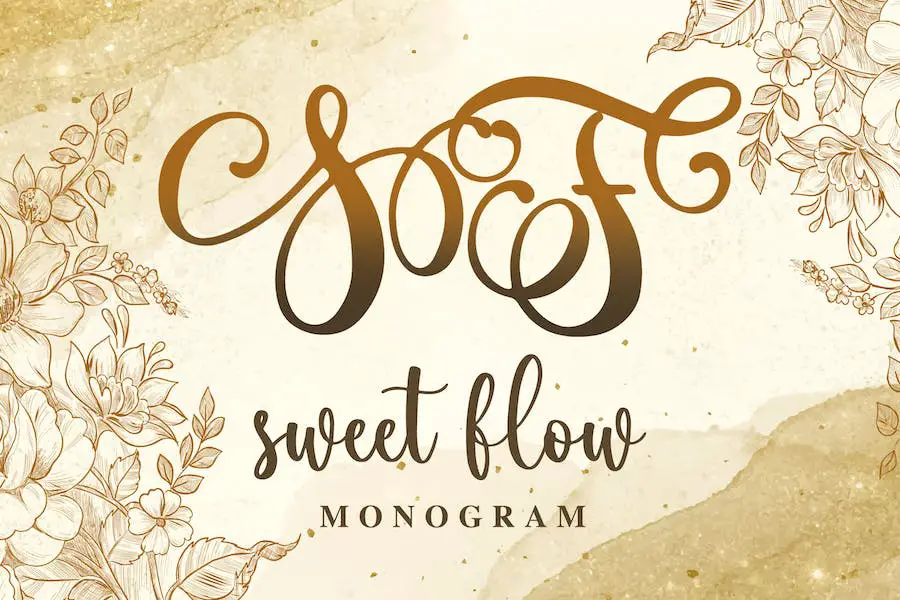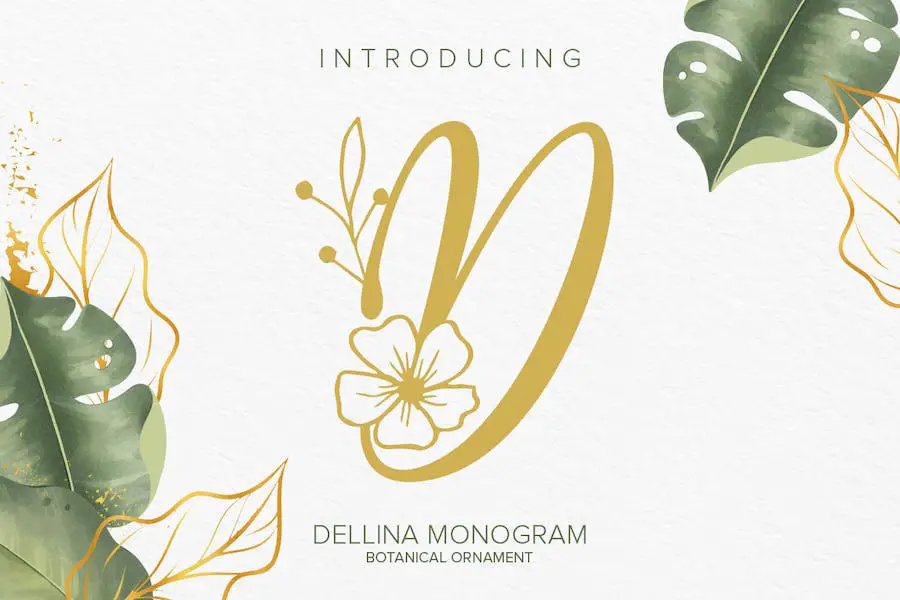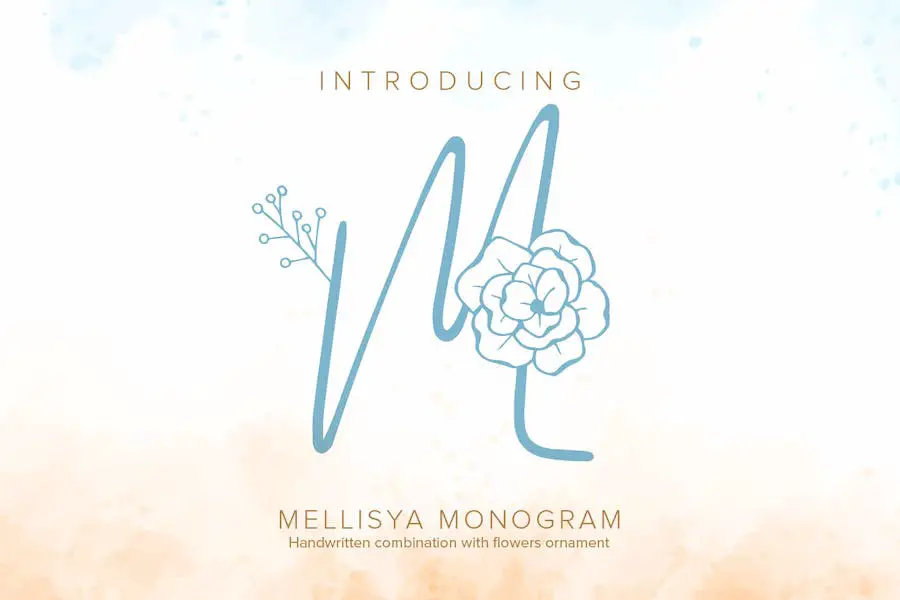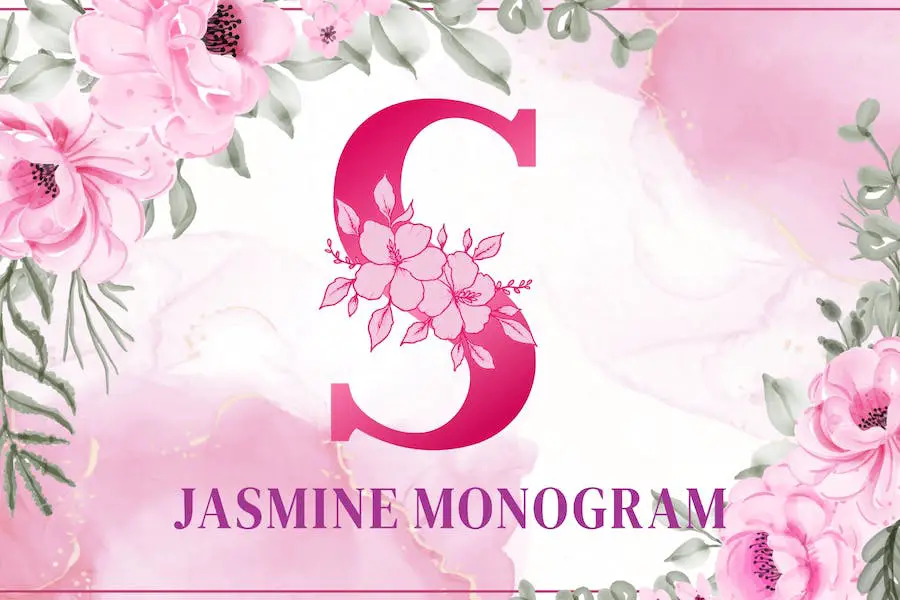
Agora, você deve estar se perguntando, por que devo considerar o uso de fontes de monograma. Bem, os monogramas têm sido uma escolha popular em design por sua elegância, sofisticação e apelo atemporal.
Eles adicionam um toque pessoal a qualquer projeto e podem elevar instantaneamente a sensação geral do seu design.
Neste artigo, não apenas mostraremos 39 das melhores fontes de monograma, mas também forneceremos algumas estatísticas e fatos interessantes sobre cada fonte.
Vamos nos aprofundar em suas origens e nos designers por trás deles, e dar a você um vislumbre de como eles podem ser usados de maneira eficaz em vários projetos de design.
Portanto, esteja você trabalhando em um logotipo, convite de casamento ou materiais de marca, essas fontes de monograma certamente inspirarão e aprimorarão seu trabalho.
Clarissa Monograma
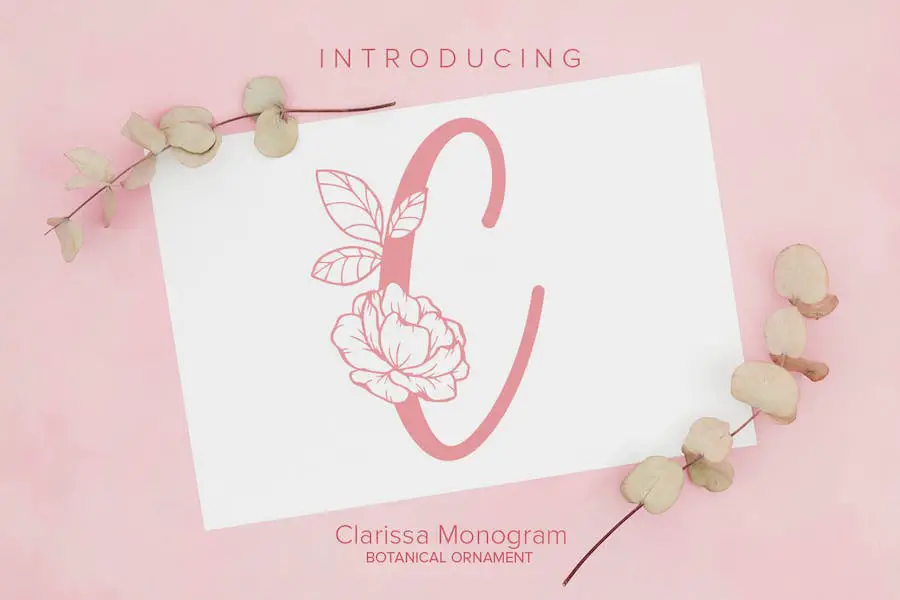
Apresentando Clarissa Monogram, uma fonte decorativa doce e delicada que pode adicionar uma sensação autêntica aos seus projetos de design.
Esteja você criando convites de casamento deslumbrantes, belas artes estacionárias, postagens de mídia social atraentes ou cartões fofos, essa fonte com certeza elevará seus designs.
Clarissa Monogram é perfeita para designers gráficos que procuram uma fonte que aprimore seus projetos e lhes dê um toque único. Com seu toque autêntico e design delicado, essa fonte é versátil e pode ser usada para diversos fins.
Caligrafia do monograma
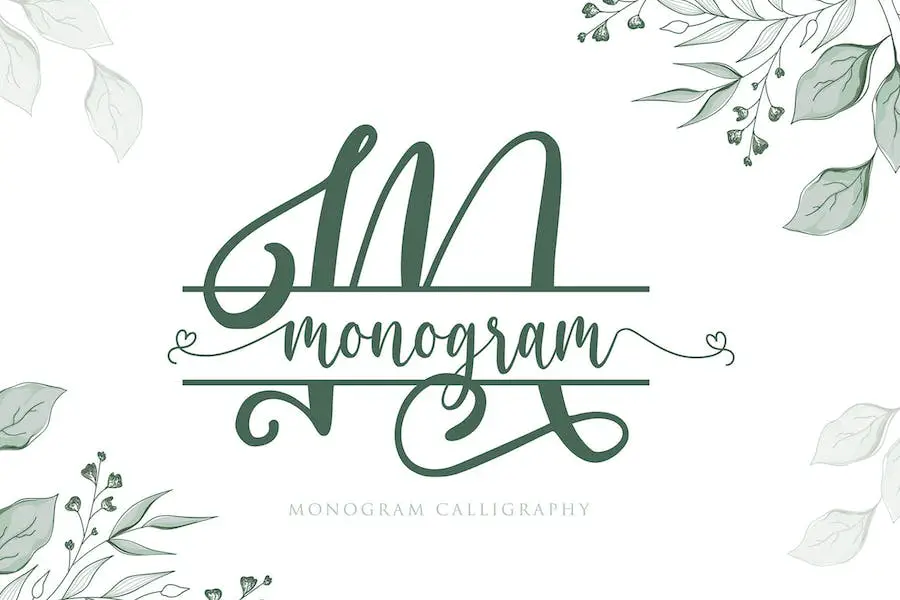
Monogram Calligraphy é uma fonte requintada que exala romance e elegância atemporal. Ele combina perfeitamente a caligrafia tradicional com elementos de design modernos para criar um monograma impressionante.
A melhor parte da caligrafia de monogramas é sua versatilidade. É compatível com vários softwares, como Google, Adobe, Word, Canva, Circuit e Figma, e até mesmo para desenhos de tatuagens e logotipos personalizados no Instagram.
Seja você um designer gráfico trabalhando em um projeto profissional ou um indivíduo procurando aprimorar sua marca pessoal, essa fonte é perfeita para você.
Casa de fazenda
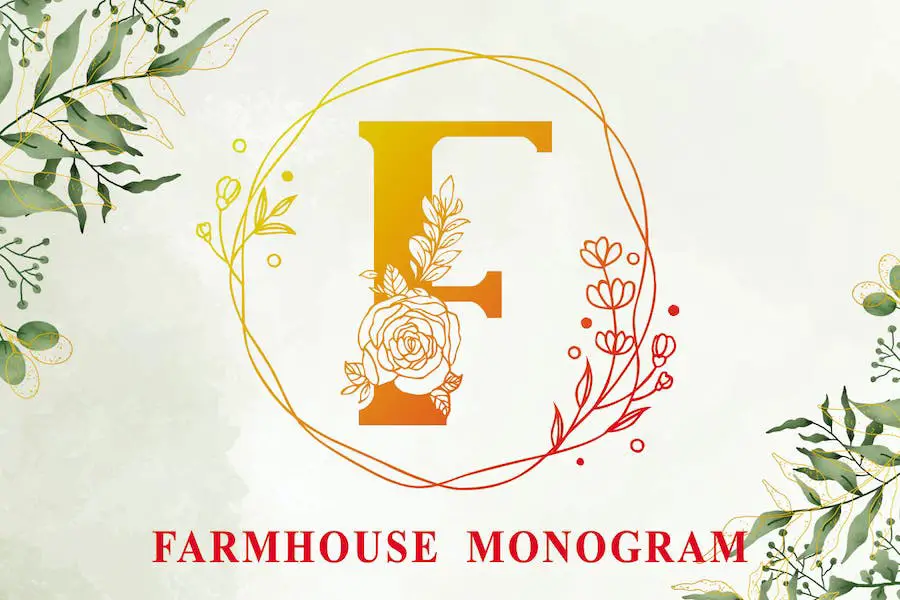
Farmhouse é uma fonte de monograma encantadora que adiciona um toque encantador a qualquer projeto de artesanato. Independentemente de você usá-la em conjunto ou separadamente, essa fonte traz uma vibração chique e alegre aos seus designs. É perfeito para adicionar um visual personalizado aos seus projetos de artesanato.
Um dos grandes recursos do Farmhouse é a codificação PUA, que permite acessar facilmente todos os glifos e ligaduras exclusivos. Isso significa que você tem ainda mais possibilidades de design ao seu alcance.
Monogram World Deco
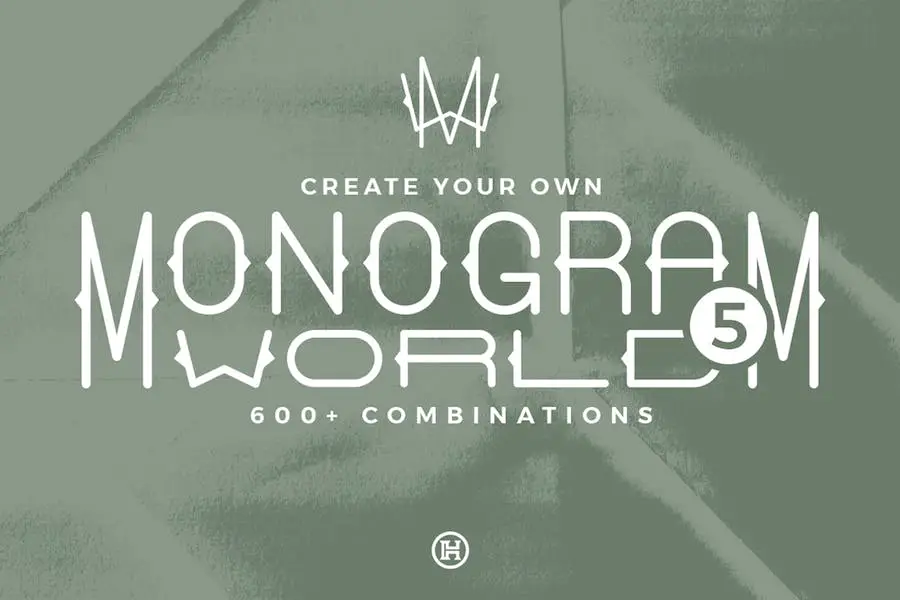
Monogram World Deco é uma fantástica fonte sem serifa projetada especificamente para ajudá-lo a criar monogramas impressionantes de forma rápida e sem esforço.
Com dois pesos disponíveis, Light e Regular, e caracteres maiúsculos e maiúsculos ligeiramente decorados, esta fonte oferece infinitas combinações para seus designs de monograma.
As letras maiúsculas são altas e estreitas, enquanto as minúsculas são mais largas e curtas no corpo, permitindo combinações perfeitas.
Dia dos namorados do monograma
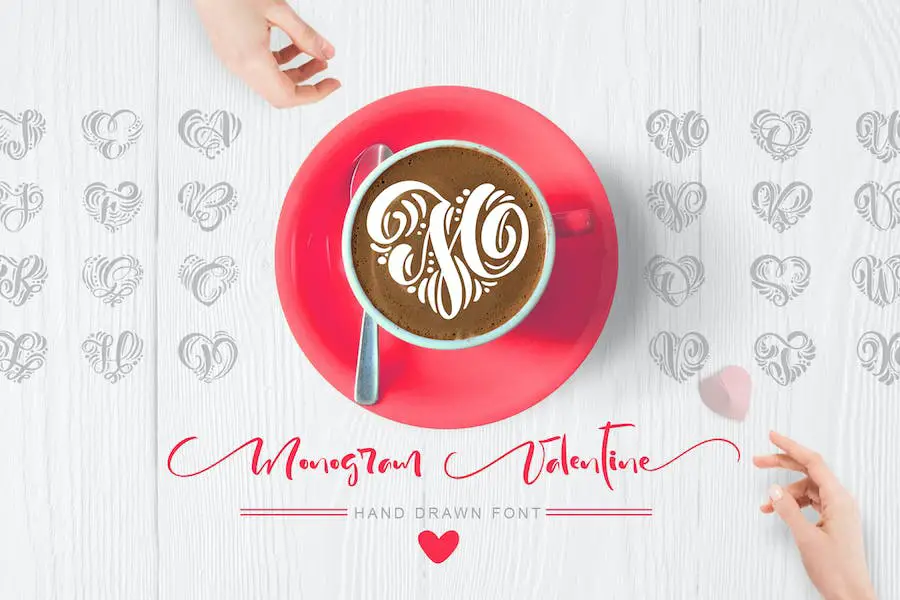
Monogram Valentine é uma bela fonte que adiciona um toque de romance e amor a qualquer projeto.
Ele apresenta floreios e redemoinhos exclusivos em forma de coração, tornando-o perfeito para convites de casamento, cartões de felicitações, logotipos e muito mais. As elegantes linhas caligráficas trazem uma sensação de frescor aos seus designs feitos à mão.
Essa fonte é ideal para decorar álbuns, cartões de felicitações de casamento e feriados (como dias de Natal, aniversários e Dia dos Namorados), logotipos, lojas de presentes, tags e até apresentações em mídias sociais e lojas na Internet.
WAW
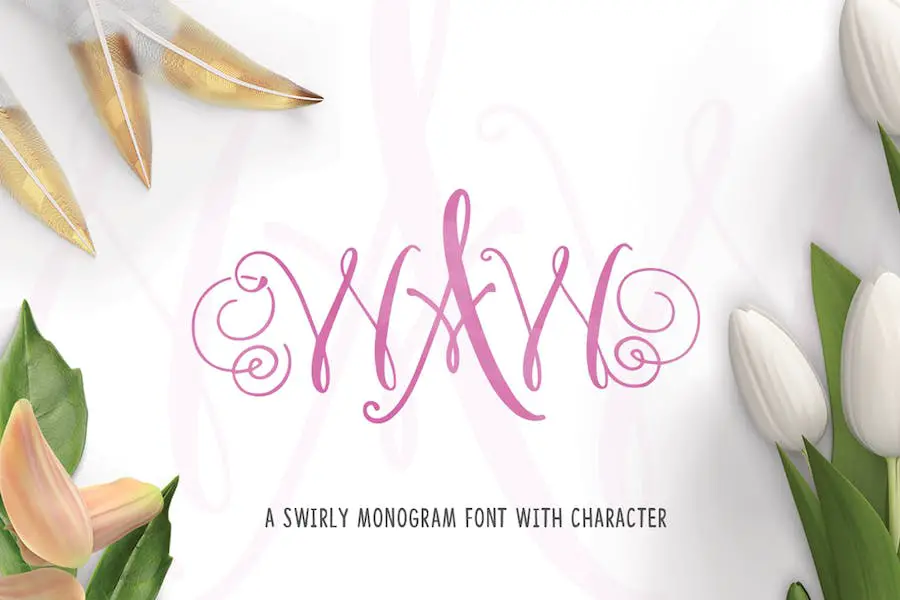
WAW é uma fonte versátil, perfeita para designers gráficos que buscam aprimorar seus projetos. Com seus dois estilos de fonte, Waw Left e Waw Right, ambos disponíveis em formato OTF e TTF, essa fonte oferece uma ampla gama de possibilidades de design.